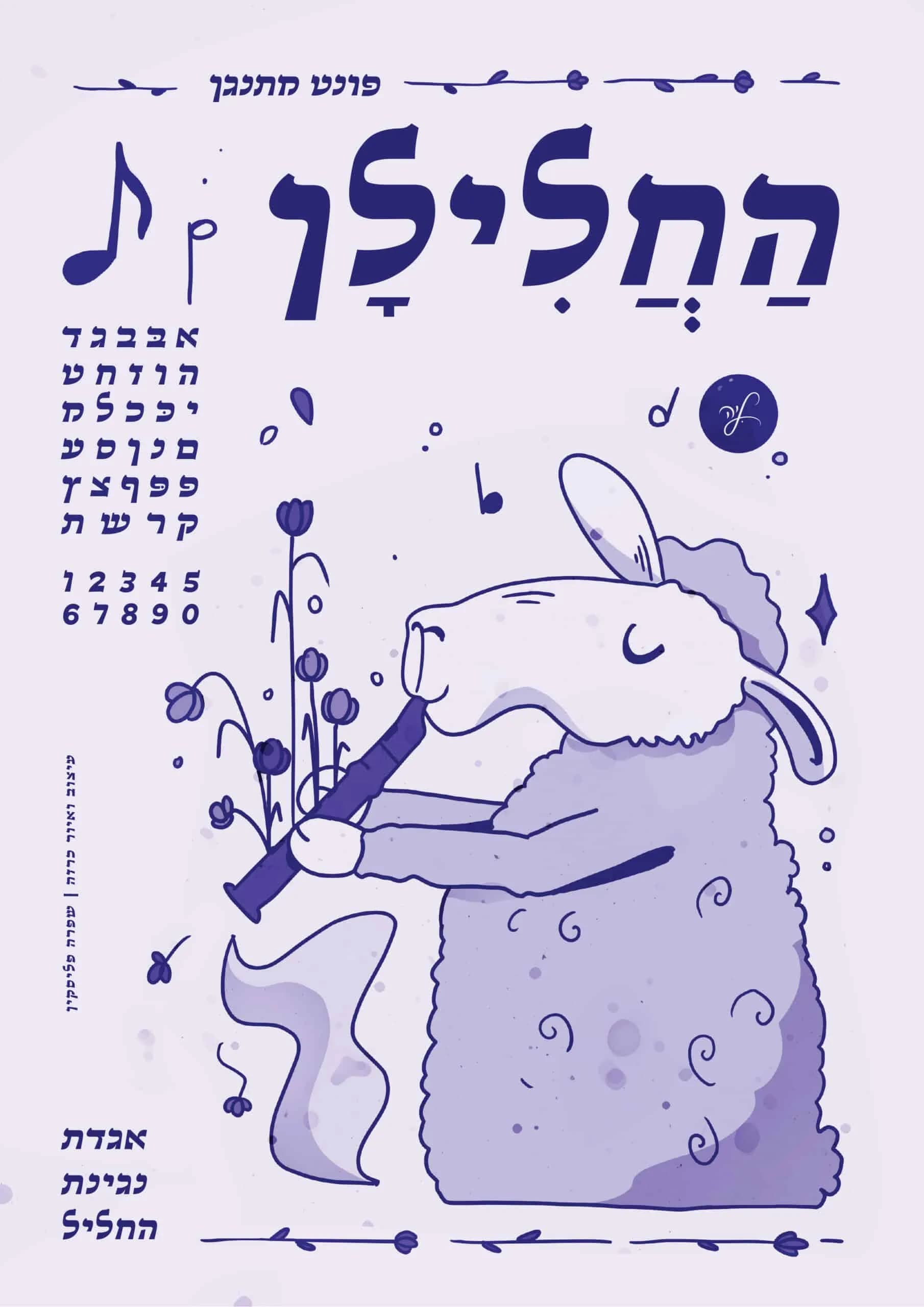
הַחֲלִילָן 🎼 בהשראת המנגינות הקסומות שמנגן חלילן, הגופן הזה מעביר את הקוראים לעולם של מנגינות ורגשות. הקווים החלקים והקצוות המעוגלים שלו יוצרים תחושת קצב וזרימה, מחקים את התנועות החינניות של מוזיקאי מיומן, הגולש ללא מאמץ מצליל לצליל. רשימת הגליפים בפונט נסו אותי כאן | אפשרויות רכישה